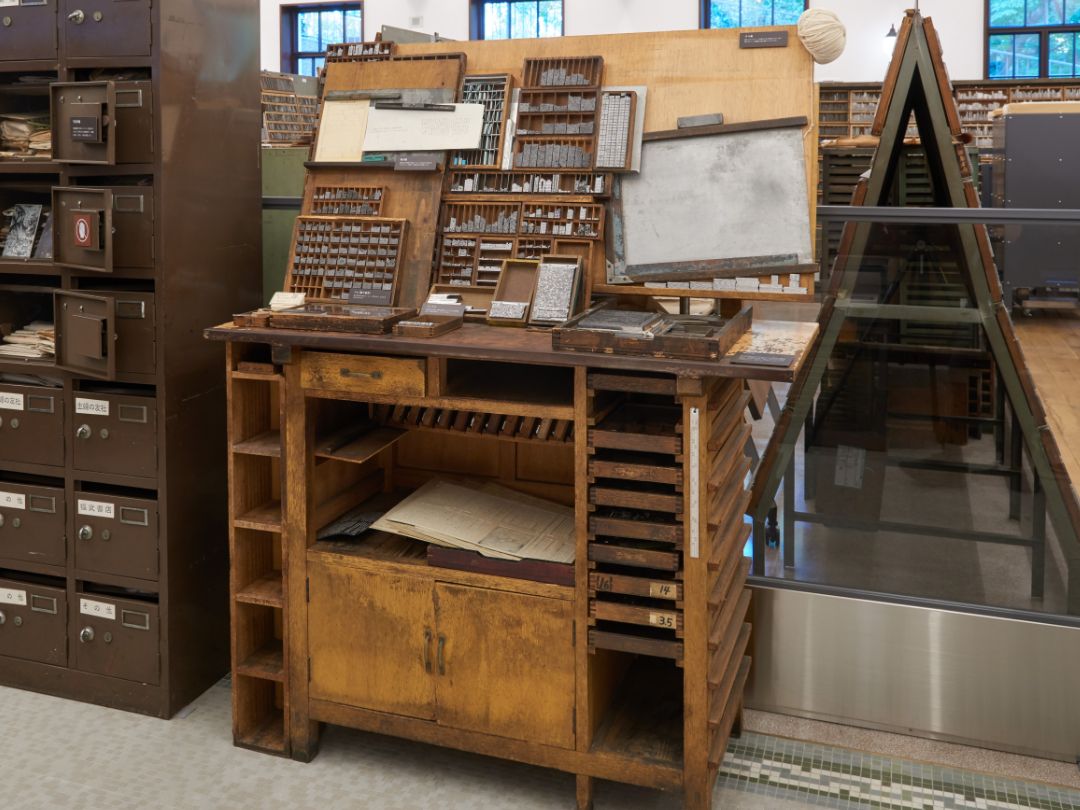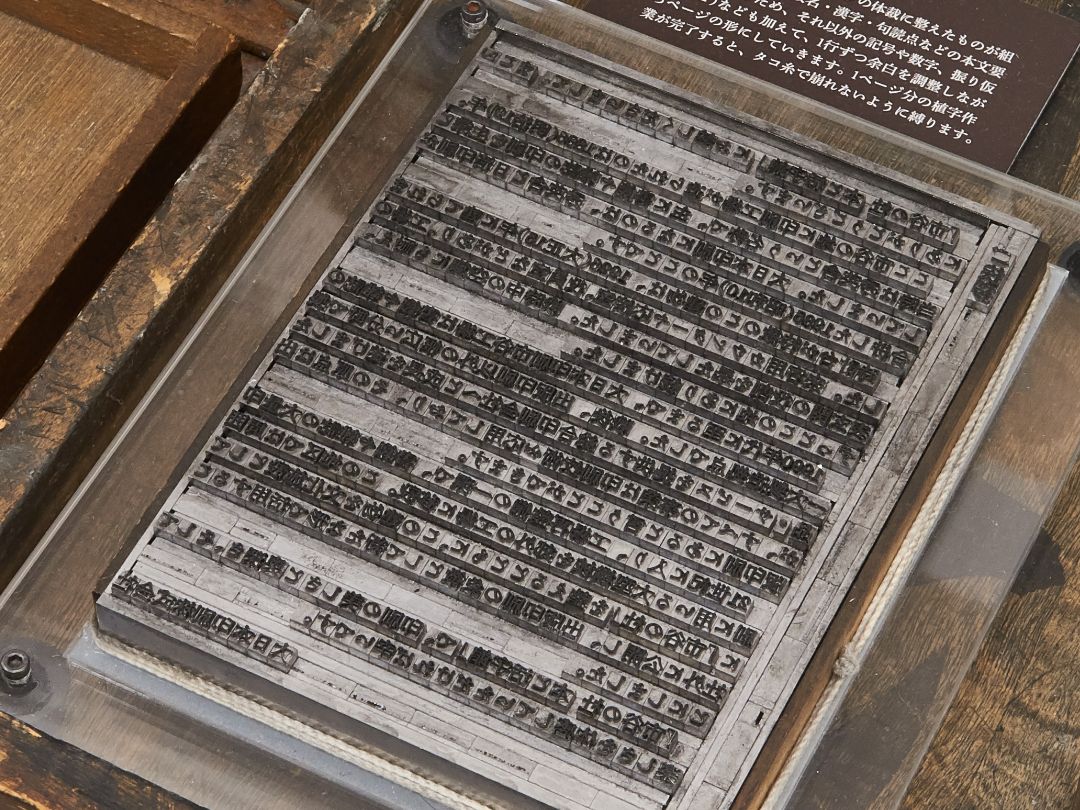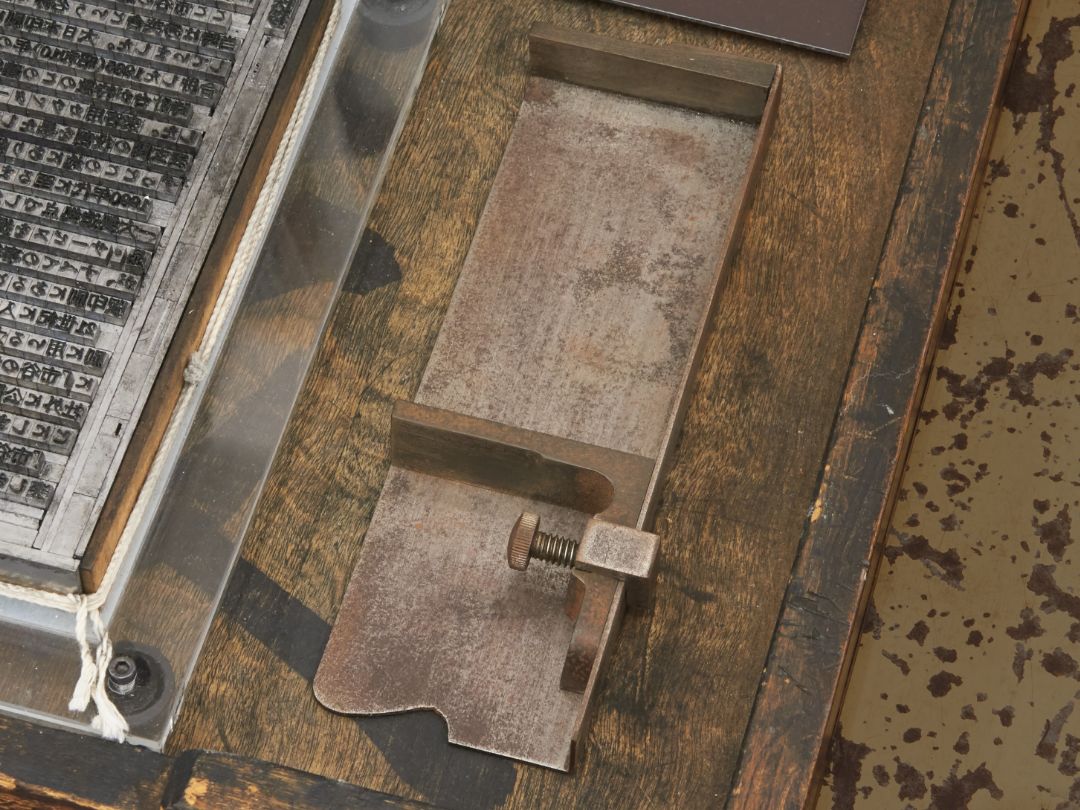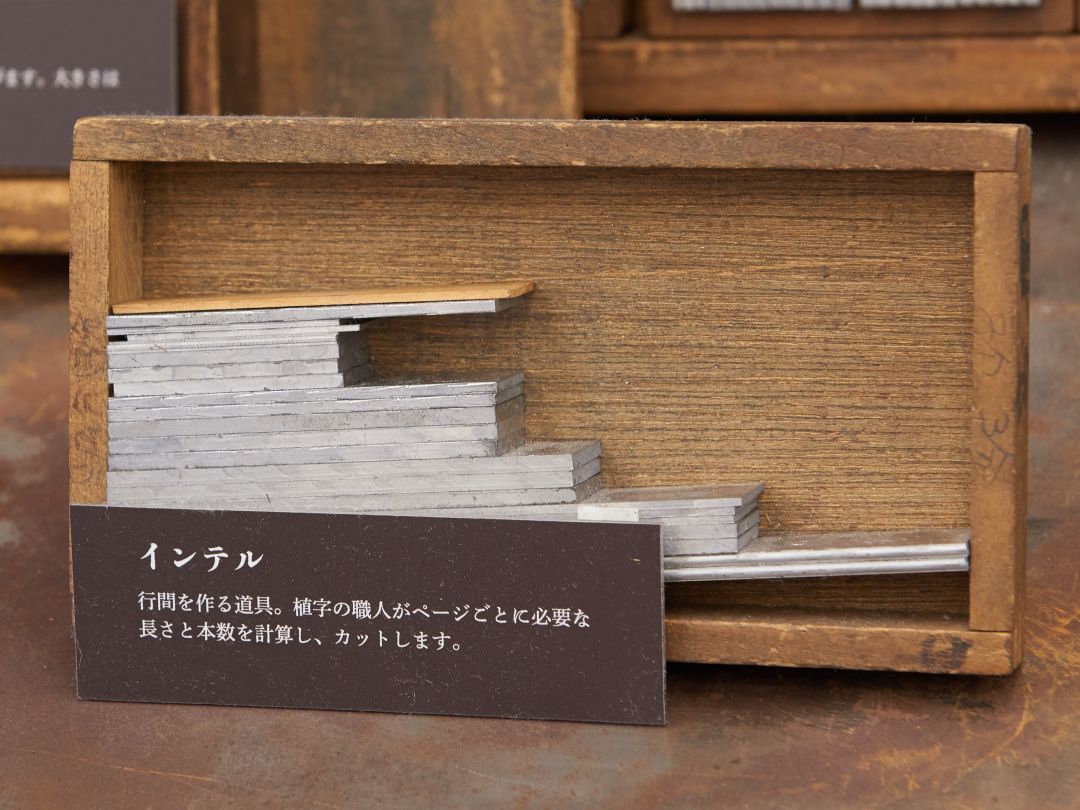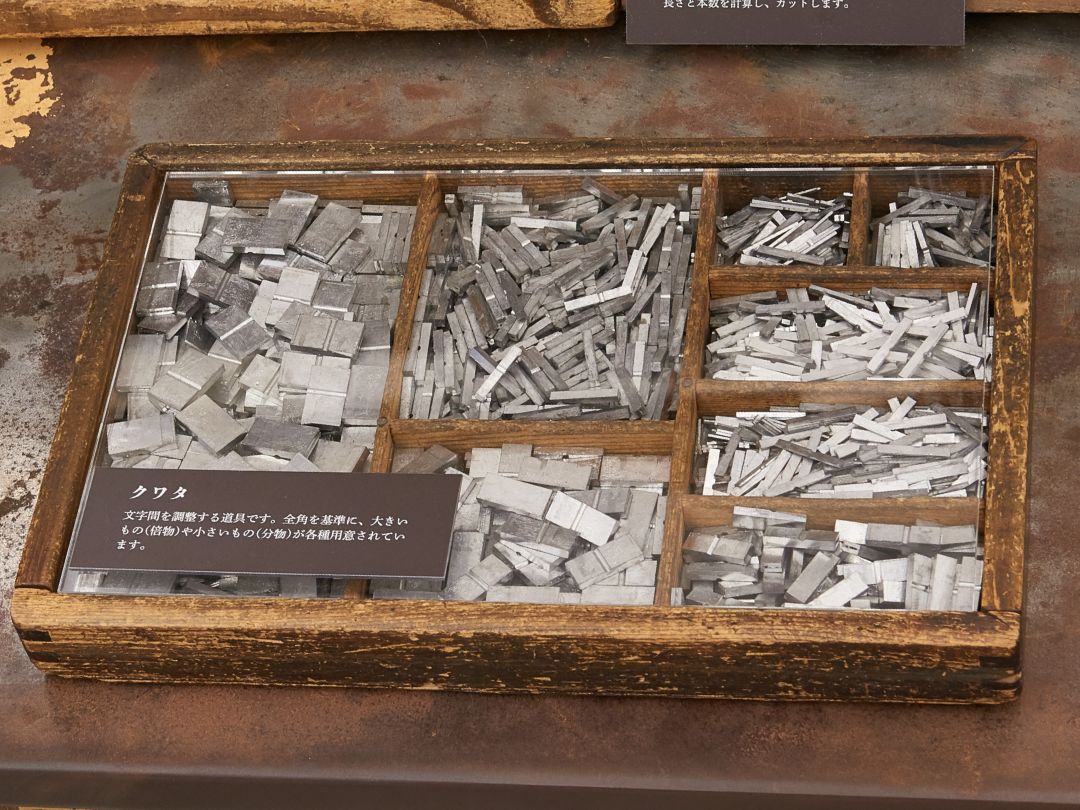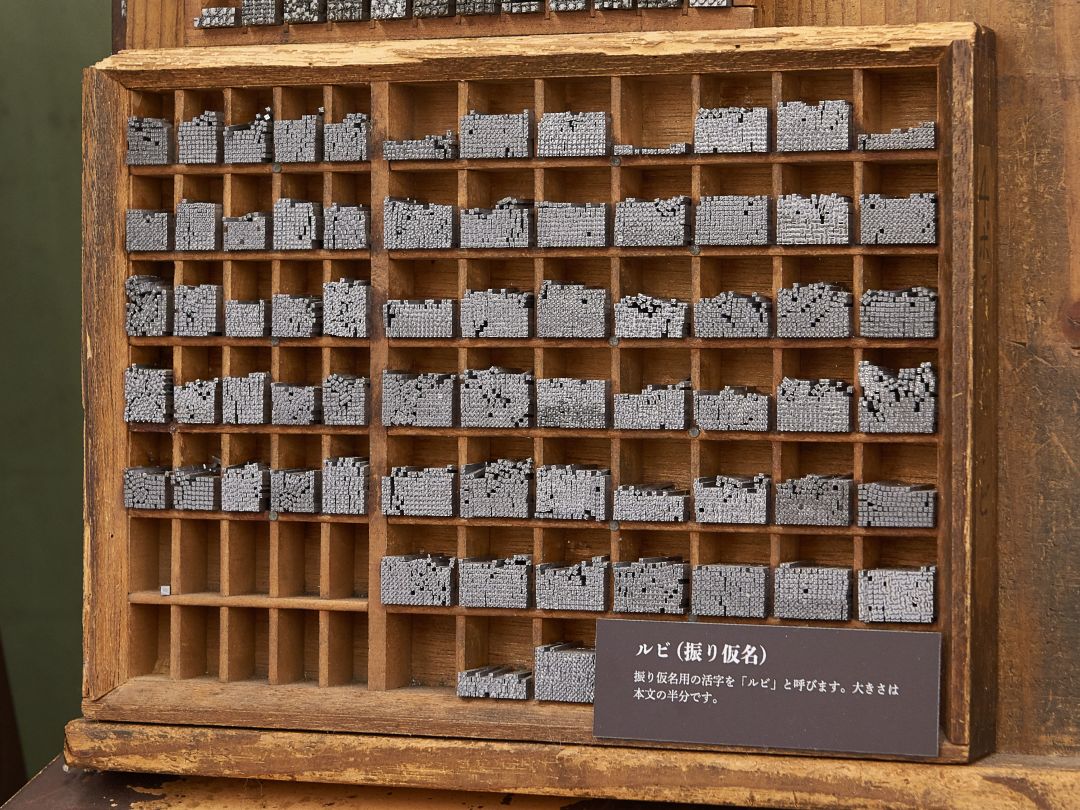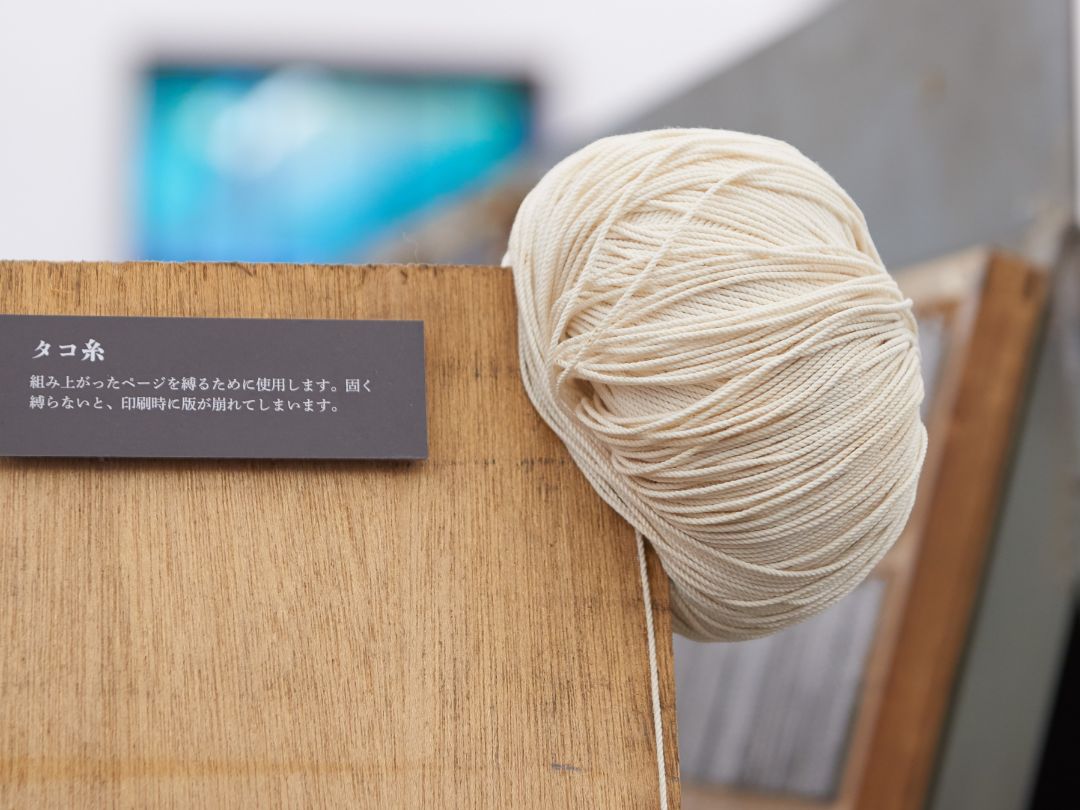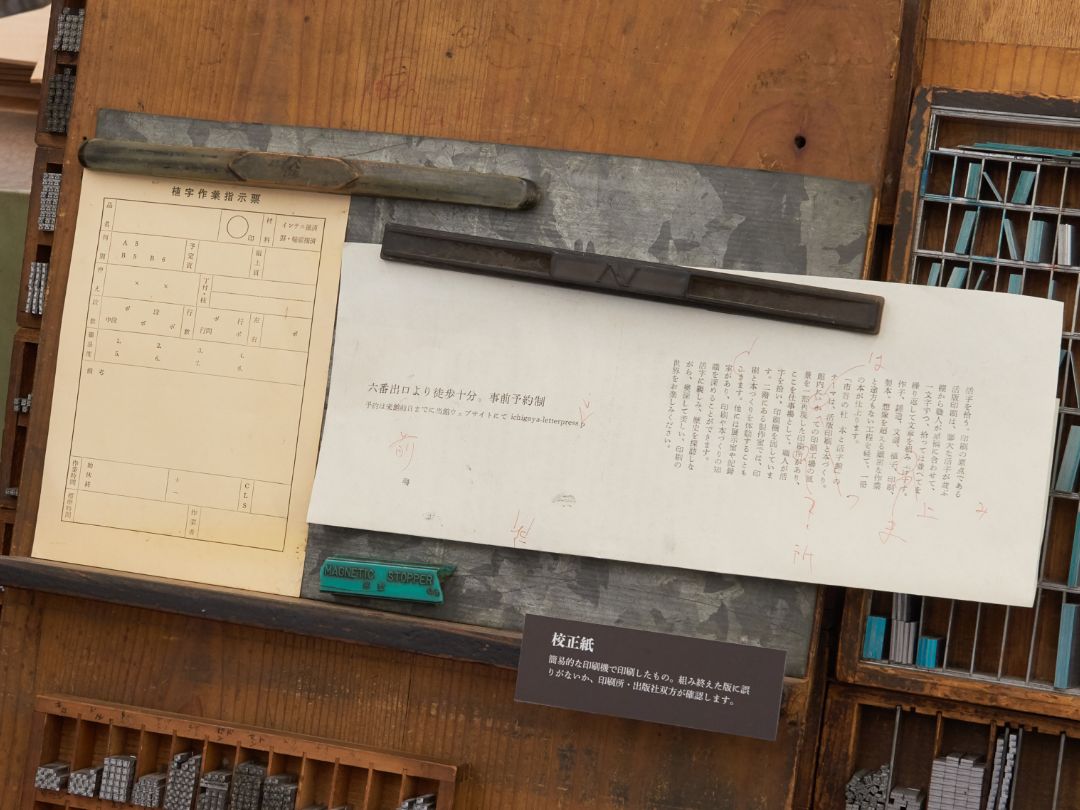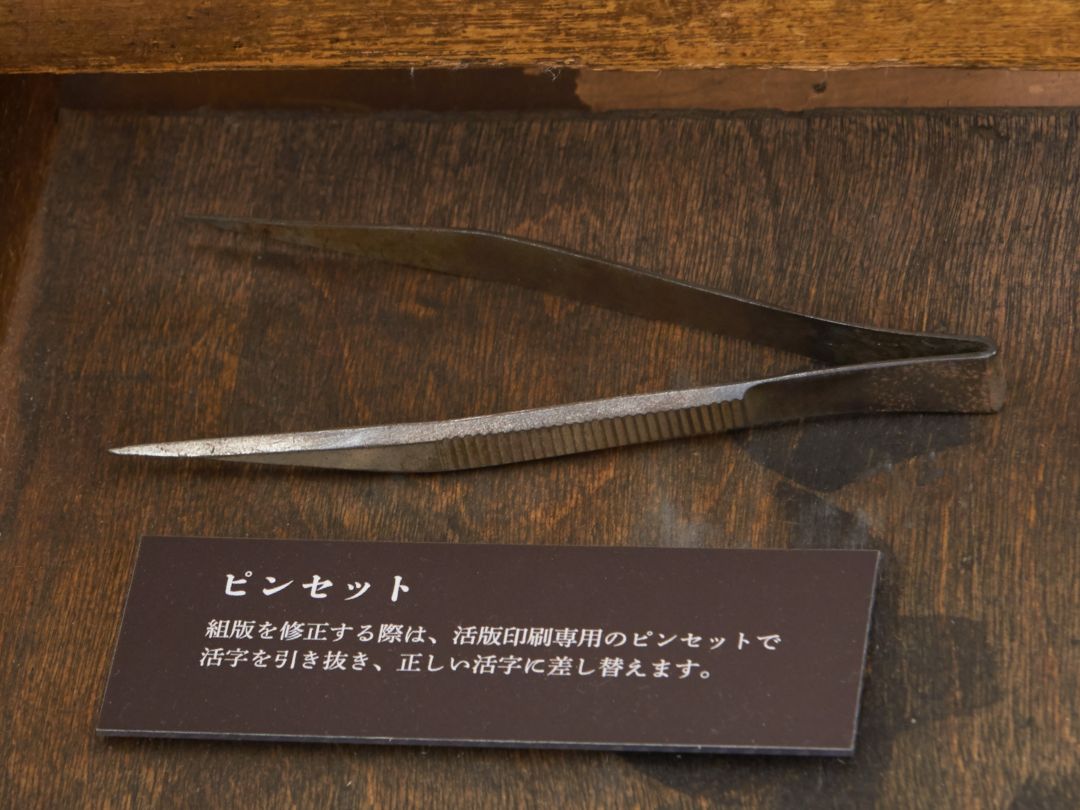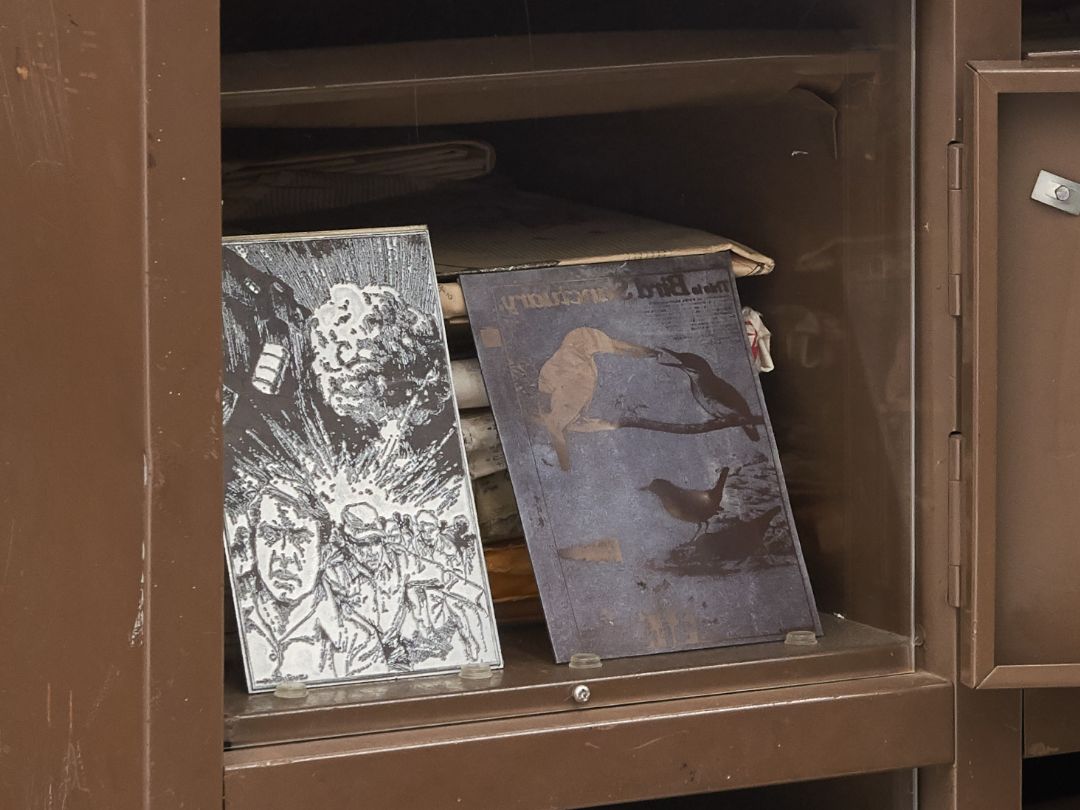
四、植字
拾った活字をページの形へと組み上げます。
拾った活字を印刷の版はんにまとめる作業が「植字ちょくじ」です。出版社が指定するページの大きさ、行数、文字数、写真や挿絵の入る位置などを踏まえてページをつくります。活版印刷では、印刷すると余白になる行間や文字間も、すべて金属で埋め尽くします。実物の版はんを見ると、その細かさに驚かされます。
植字ちょくじ台
植字ちょくじ作業のための台です。植字ちょくじの職人は自分専用の台を持ち、進行中の作業に応じて必要な道具ケースを目の前に並べて使用します。数行すうぎょうずつステッキで組んだら、台の上に積み上げてページを作っていきます。
組版
文選ぶんせんで拾った活字をページの体裁に整えたものが組版です。文選ぶんせんでは仮名かな・漢字・句読点などの本文ほんもん要素だけを拾うため、それ以外の記号や数字、振り仮名(ルビ)なども加えて、1行いちぎょうずつ余白を調整しながらページの形にしていきます。1ページ分の植字ちょくじ作業が完了すると、タコ糸で崩れないように縛ります。
ステッキ
拾った本文ほんもんの活字に行間や文字間などを挿入しながら、数行すうぎょう単位で版はんの形にするための道具。
インテル
行間を作る道具。植字ちょくじの職人がページごとに必要な長さと本数を計算し、カットします。
クワタ
文字間を調整する道具です。全角を基準に、大きいもの(倍物ばいもの)や小さいもの(分物ぶんもの)が各種用意されています。
ルビ(振り仮名)
振り仮名用の活字を「ルビ」と呼びます。大きさは本文ほんもんの半分です。
タコ糸
組み上がったページを縛るために使用します。固く縛らないと、印刷時に版はんが崩れてしまいます。
校正紙こうせいし
簡易的な印刷機で印刷したもの。組み終えた版はんに誤りがないか、印刷所・出版社双方が確認します。
ピンセット
組版を修正する際は、活版印刷専用のピンセットで活字を引き抜き、正しい活字に差し替えます。
写真凸版
活版印刷で写真やイラストを表現するための、凹凸のある金属版です。組版に貼り、活字と一緒に印刷します。